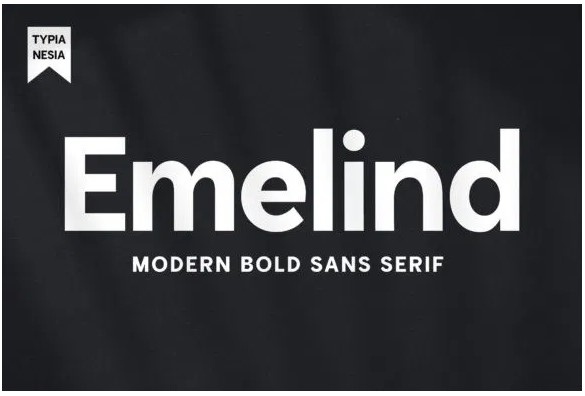
Creativefabrica Emelind Font
[Creativefabrica] Emelind Font
Эмелинда - смелый и аккуратный шрифт без засечек. Его легко подогнать под невероятно большой набор проектов, так что добавьте его к вашим творческим идеям и заметьте, как он выделяет их на фоне других!